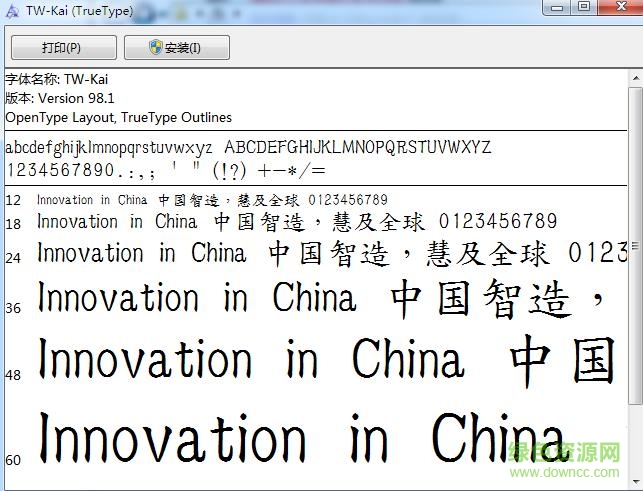
全字庫正楷體是臺(tái)灣全字庫系列字體中的一款,字體端正、大氣,給人非常正規(guī)的感覺,有喜歡楷體字體的朋友可以來下載使用!
全字庫正楷體是采用正楷體打造的一款電腦字體,字體端正大方得體,筆畫鏗鏘有力,整體效果非常的漂亮,字體筆畫細(xì)膩,非常的優(yōu)雅,可進(jìn)行中英文和阿拉伯?dāng)?shù)字的輸入!